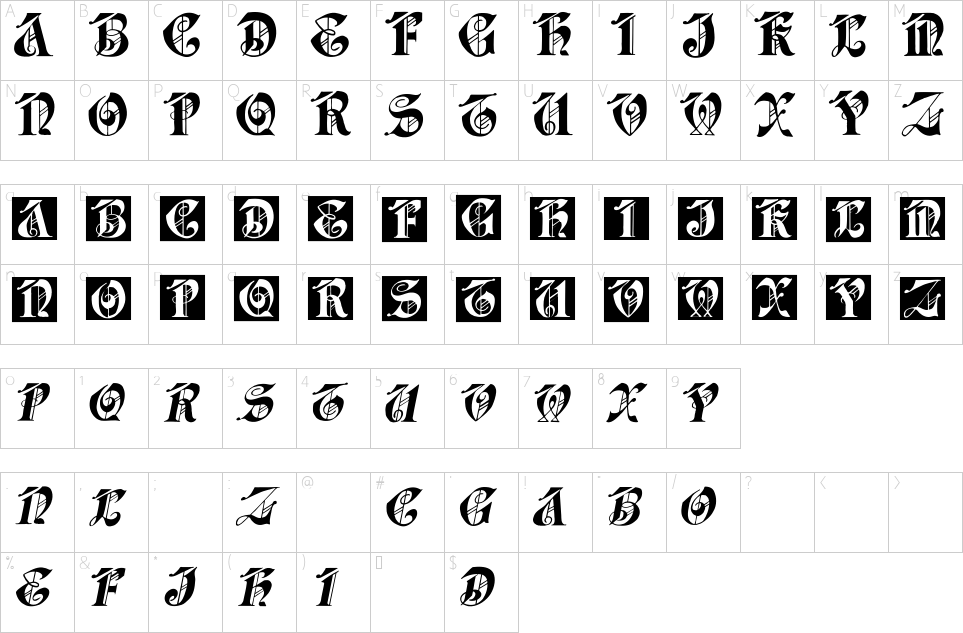
Dolby Frax Caps Font – Download Grátis
A Dolby Frax Caps é uma elegante fonte caps que adiciona um toque moderno a seus projetos digitais. Desenvolvida pelo talentoso designer Manfred Klein 几个字的翻译, esta font oferece um equilíbrio perfeito entre estilo e legibilidade, ideal para nomes de negócios ou marcas. Ela pode ser facilmente usada em qualquer plataforma, seja Windows ou Mac, garantindo que a aparência da sua identidade visual seja uniforme independentemente do sistema operacional utilizado. Com seu design cuidadosamente pensado por Manfred Klein, esta fonte oferece uma opção de alta qualidade para quem busca estilizar textos sem comprometer a leitura fácil. Dolby Frax Caps está disponível gratuitamente e é uma das muitas opções disponíveis no site dedicado à compartilhação de fontes de qualidade. Seja para projetos pessoais ou profissionais, esta fonte traz um toque sofisticado e moderno a qualquer trabalho que você esteja desenvolvendo. Não perca essa oportunidade de adicionar um toque único a seus materiais digitais, seja através da escolha da sua fonte ou dos outros recursos oferecidos pelo site que suporta e promove o uso livre de fontes de alta qualidade.